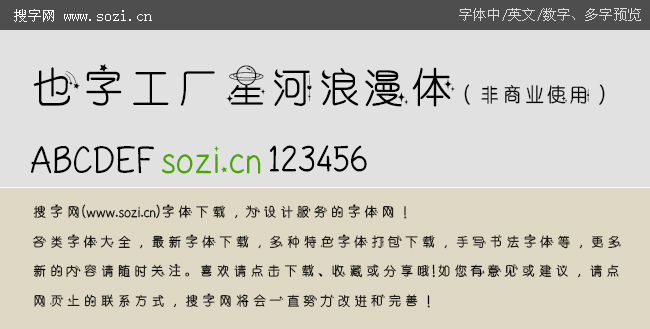
也字工廠星河浪漫體
搜字網給大家提供一款也字工廠星河浪漫體(非商業(yè)使用)中文字體下載,也字工廠星河浪漫體是一款卡通風格的字體,字形可愛,又帶有卡通圖案裝飾,非常有趣味性。適合應用于兒童繪本、兒童海報、網頁設計等應用(此字體為個人非商用版,商用可以聯(lián)系:官方網址:https://yefont.com/home,聯(lián)系方式:13798980448)。